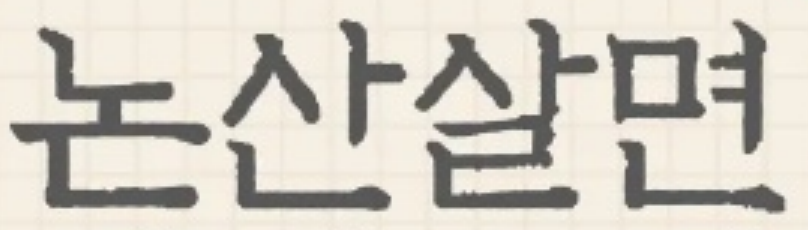
명조? 옛날 명조인가요 ㅠㅜ wor*** 2024.02.08 무슨 폰트인지 너무 궁금합니다 ㅠㅜ 댓글 0 등록 sta*** ON 여씨향약언해 같네요 https://www.sandollcloud.com/font/16489.html 2024-02-08 답글 달기 댓글 더보기 쉽고 빠르게 가장 비슷한 폰트를 알고 싶다면? 이미지로 검색하기
ON 여씨향약언해 같네요 https://www.sandollcloud.com/font/16489.html